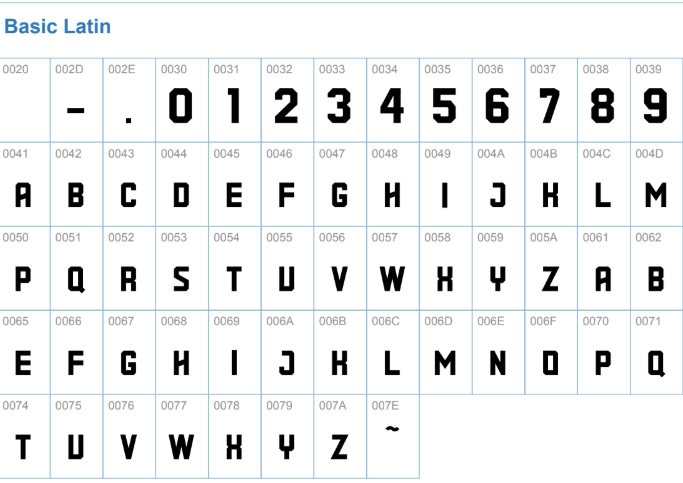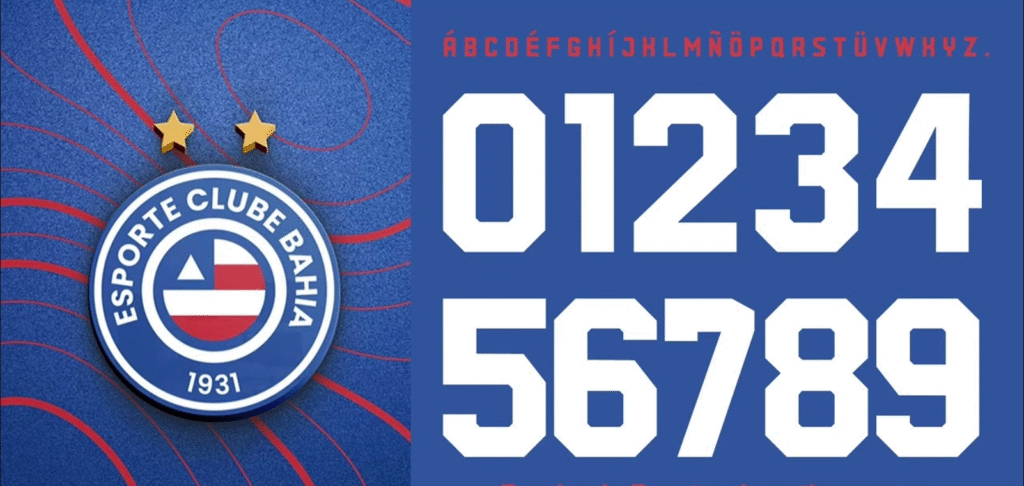
O Esporte Clube Bahia vive um momento de pura vibração e modernidade. Com a temporada 2024 a todo vapor e a parceria com o City Football Group, a identidade visual do clube evoluiu, e a tipografia usada nas camisas do Esquadrão de Aço é um reflexo direto disso.
Seja para criar artes para a torcida, personalizar um mockup ou simplesmente para estudar o design do seu time do coração, ter a fonte correta é essencial. E é exatamente isso que trazemos para você hoje: a fonte oficial usada pelo Bahia em seus uniformes de 2024.
O Estilo Visual: Força e Modernidade
A tipografia do Bahia para 2024 é marcada por um design que equilibra força e vanguarda. As letras possuem um formato robusto e geométrico, com cortes precisos que garantem excelente legibilidade, seja no campo ou nas transmissões de TV.
Diferente de fontes genéricas, ela foi desenhada para impor respeito, transmitindo a energia da torcida tricolor e a nova fase moderna do clube. É uma fonte que “grita” futebol e performance, vista claramente nas costas dos jogadores do Esquadrão em todas as competições.